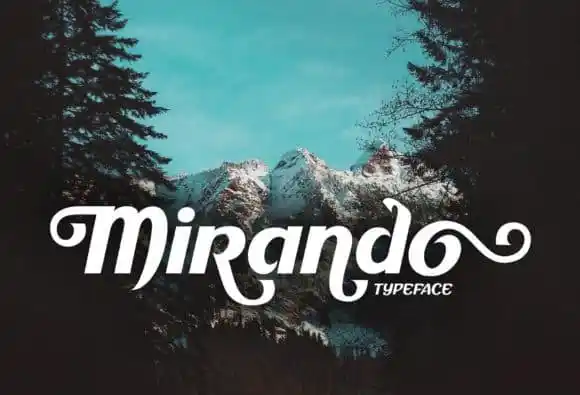
Mirando Display Font – Download Grátis
A Mirando Display Font é uma família de fontes para ambientes de visualização que foi criada especificamente para a publicação “Caos Sagrado”. Este projeto especialmente concebido abrange fanzines e revistas informativas, onde seu design minimalista mas elegante atinge perfeitamente o objetivo de destaque. Desenvolvida pelo designer Cove703 na plataforma 99designs, a Mirando é uma fonte de visualização ideal para uma ampla gama de aplicações gráficas. Suas linhas simples e limpas tornam a Mirando acessível para um vasto leque de projetos, garantindo que seja uma opção preferencial em qualquer projeto. Seja no design de posters, em cartazes ou mesmo nas páginas internas dos seus mais elaborados fanzines, a Mirando oferece um estilo impecável para qualquer ocasião. Sua simplicidade faz da Mirando uma fonte versátil que se destaca entre as muitas opções disponíveis no mercado.